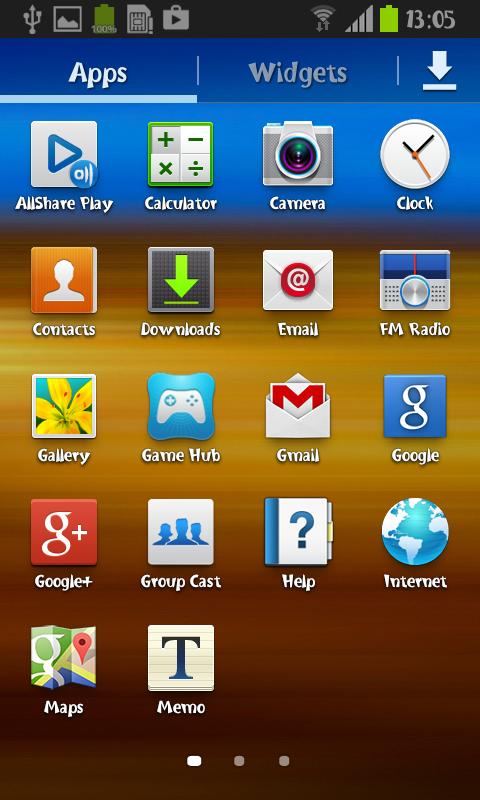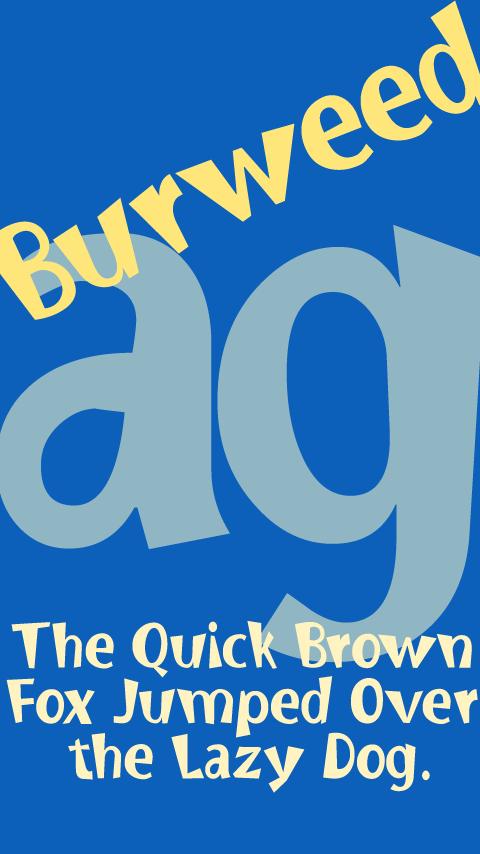
Über Burweed FlipFont
Burweed ™ Latin FlipFont
Die Burweed ™ Schrift ist ein Bildersturm, in-your-face-Design. Wenn Sie ein Hardcore-Gamer oder Hip-Hop-Liebhaber sind, ist dies der Schrift für Sie.
Pan-European-Zeichensatz
unterstützt die west-, mittel- und osteuropäischen Sprachen.